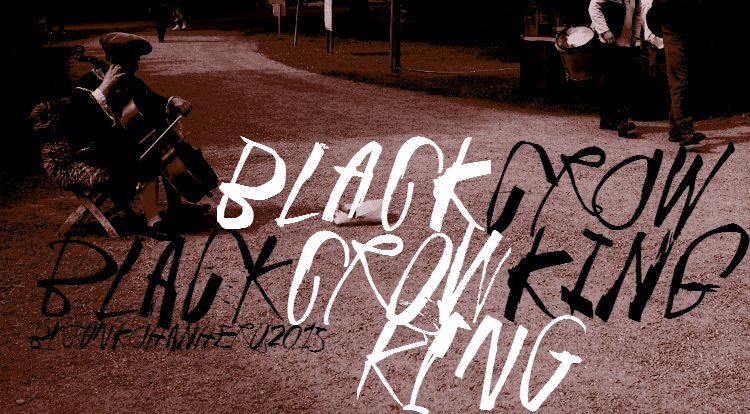
Aqui está uma breve e envolvente descrição para a página de download da fonte ‘Black Crow King Font Family’, seguindo as regras fornecidas: Esta elegante e original fonte script, criada pelo designer austríaco Juha Korhonen, é perfeita tanto para projetos pessoais quanto comerciais. Com um estilo poderoso que transmite confiabilidade e autoridade, esta família de fontes é ideal para nomes e logotipos profissionais. O Black Crow King Font Family oferece uma variedade de opções personalizáveis, desde o título até as fontes do corpo do texto. Se você está procurando uma fonte que transmita força e destaque ao seu projeto, esta pode ser a solução perfeita. Além disso, designers profissionais têm a opção de adquirir uma licença comercial por um simples pagamento online, garantindo o uso ilimitado e seguro desta incrível fonte. Para aqueles que valorizam contribuições voluntárias, também existe uma forma fácil de doar, caso esteja em sintonia com o conceito de compartilhamento de talentos. Não importa qual sua prioridade, a Black Crow King Font Family está aqui para complementar seu projeto e dar um toque único ao design.